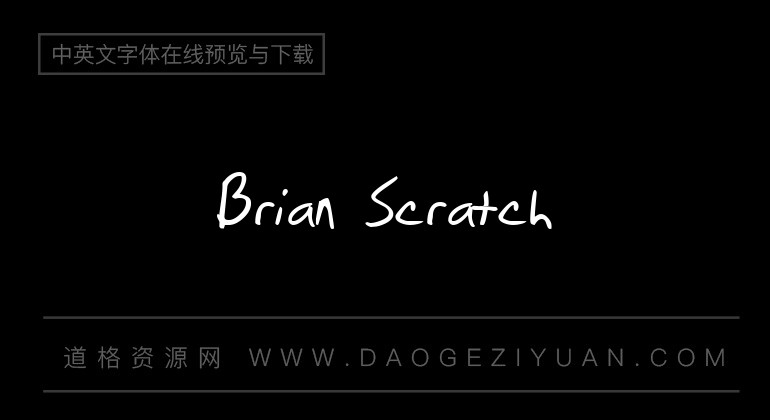
Brian Scratch 字体是一款英文手写体字体,由英国设计师 Brian Scratch 创作。它是一种自然、朴素的手写体字体,有着温暖、友善的气息,适合用于各种宣传海报、书册等设计中。它的字体结构简单,斜体和粗体的组合可以给设计师带来更多的创作灵感。内容介绍
Brian Scratch是一款非常不错的手写艺术字体,具有很好的视觉感,适合于文化类的宣传设计、商业类品牌的广告和产品包装设计以及个性化文字排版等较多场景。